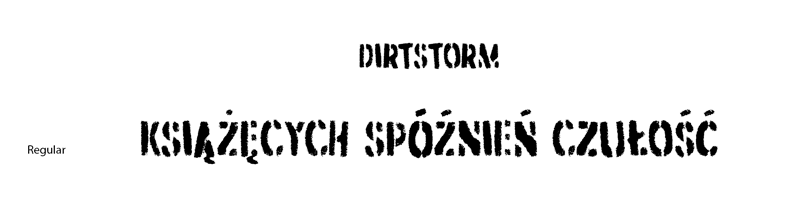
Font Dirtstorm
Zakupiliśmy ozdobny font Dirtstorm, zaprojektowany w 2007 roku przez Raya Larabie z Japonii. Litery mają charakterystyczne kształt znaków namalowanych sprayem przy użyciu szablonu.